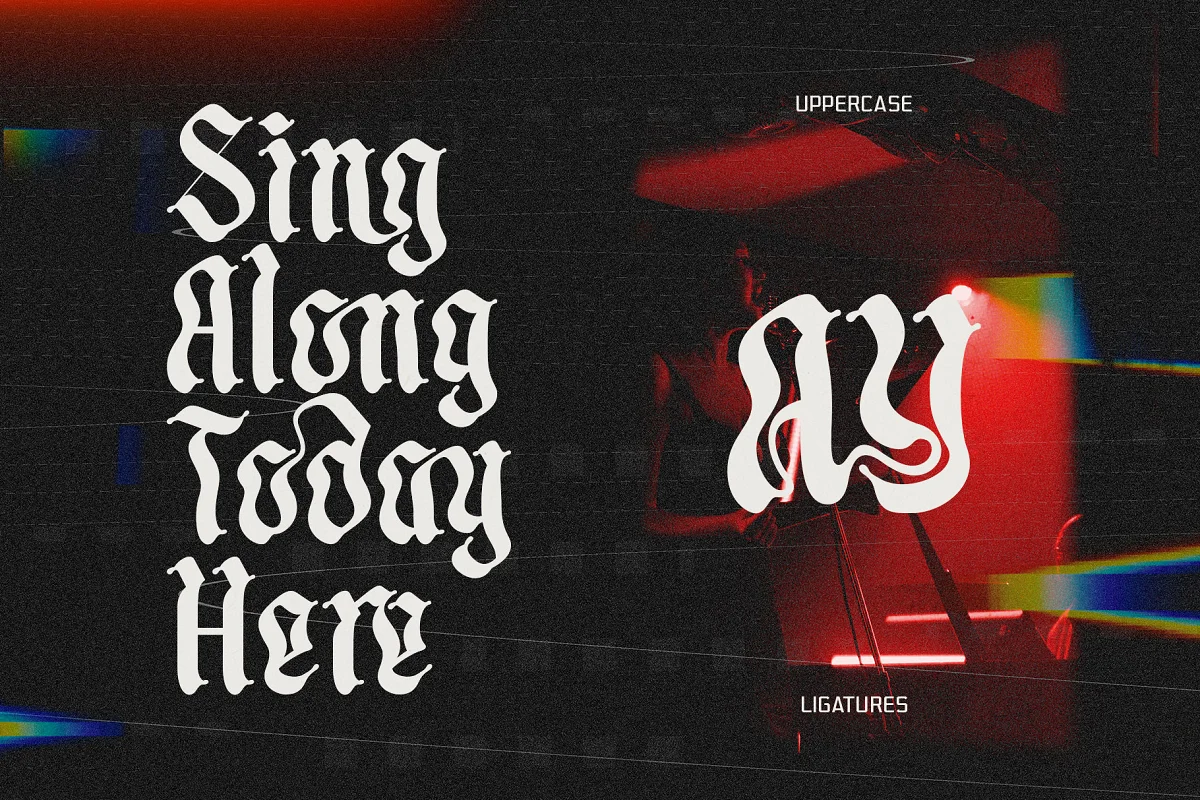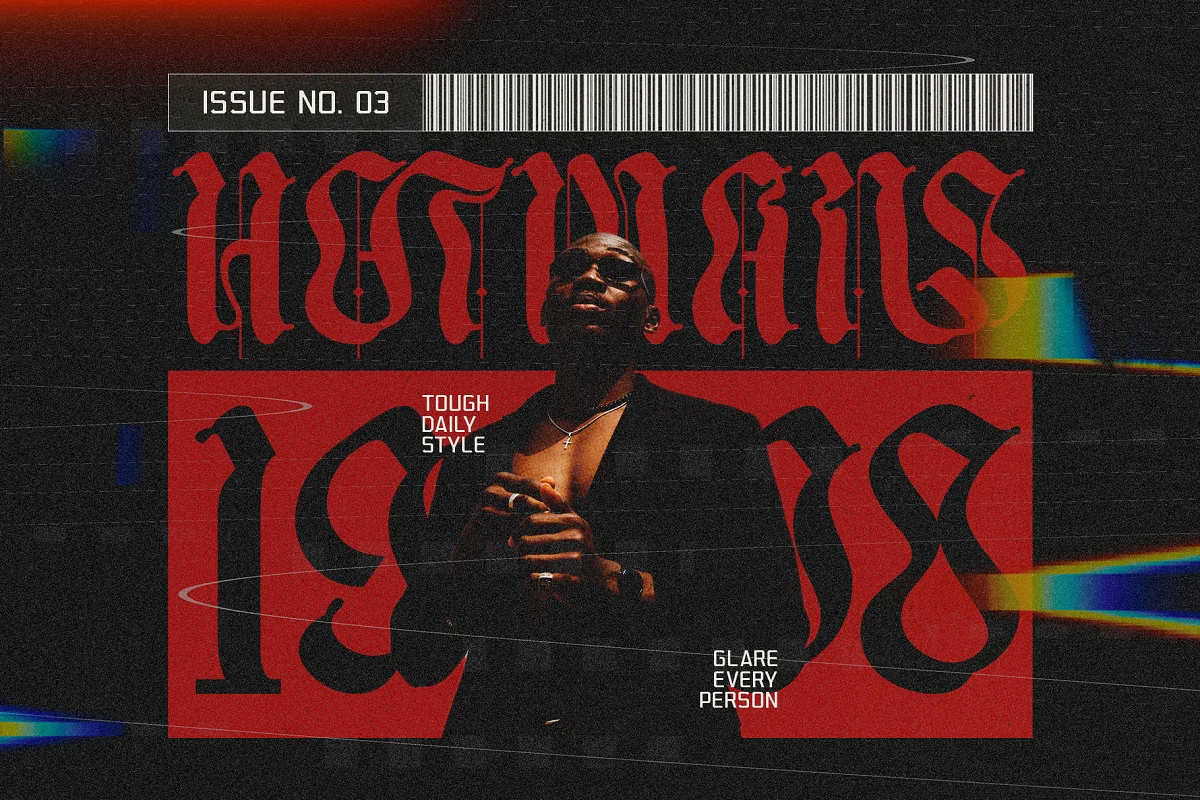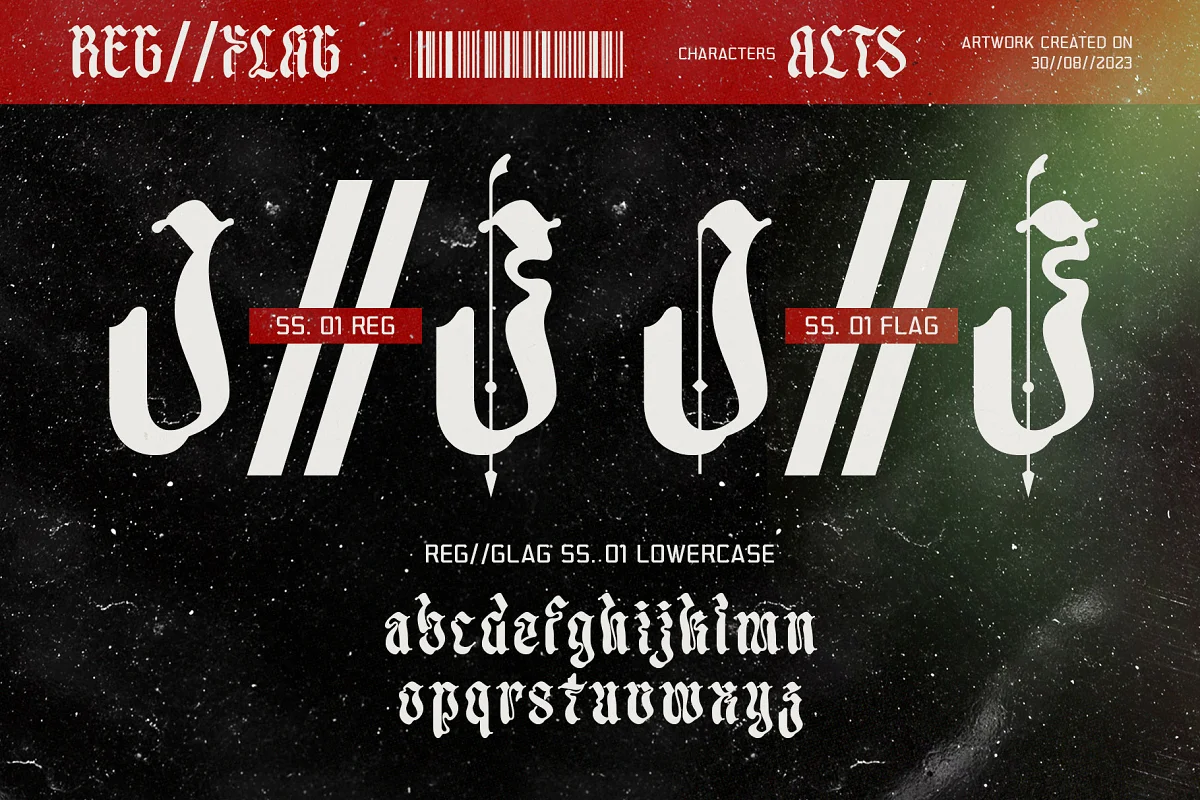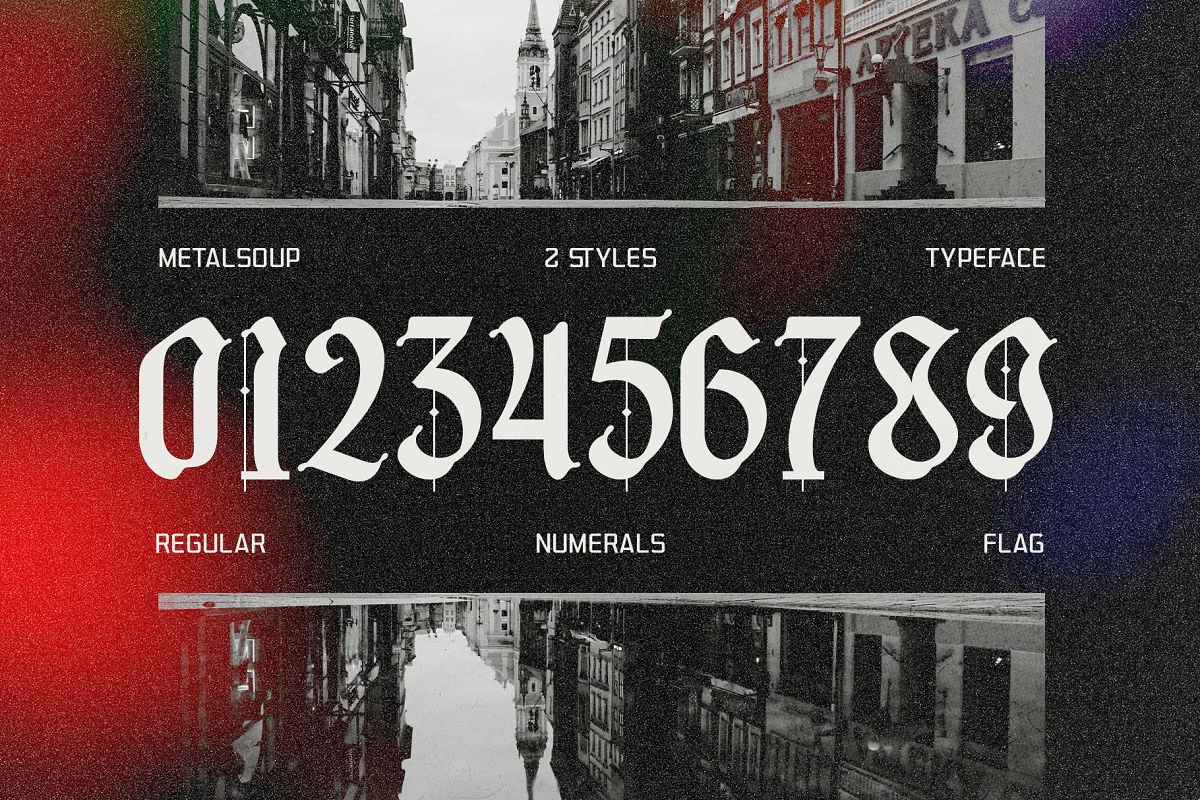
“Metal Soup” là một phông chữ blackletter quyến rũ, toát lên sự pha trộn độc đáo giữa sự táo bạo và nét thẩm mỹ năng động, tinh tế. Với thiết kế mạnh mẽ, phông chữ này hoàn hảo để tạo ấn tượng nổi bật trong các dự án thiết kế của bạn. “Metal Soup” tự hào có 720 ký tự và cung cấp hỗ trợ đa ngôn ngữ toàn diện, làm cho nó trở nên linh hoạt và có thể thích ứng với nhiều ứng dụng sáng tạo.
Các tính năng chính:
Kiểu chữ đen: “Metal Soup” có thiết kế chữ đen cổ điển, đặc trưng bởi những đường nét góc cạnh, sắc nét và các chi tiết trang trí công phu, mang lại cho văn bản của bạn cảm giác Gothic, thời trung cổ.
Phá hủy năng động: Phông chữ đã được chế tạo tỉ mỉ để kết hợp vẻ ngoài đau khổ, phong hóa. Mỗi chữ cái vẫn giữ được tính toàn vẹn trong khi vẫn có vẻ dũng cảm và hư hỏng, bổ sung thêm nét đặc trưng và cảm giác sóng độc đáo cho văn bản của bạn.
Bộ ký tự mở rộng: Với 720 ký tự, “Metal Soup” cung cấp hỗ trợ toàn diện cho nhiều ngôn ngữ và ký tự đặc biệt, đảm bảo văn bản của bạn trông tuyệt đẹp trong nhiều ngữ cảnh.
Ký tự thay thế: Phông chữ này bao gồm nhiều ký tự thay thế khác nhau, cho phép bạn thử nghiệm các dạng chữ khác nhau để đạt được tính thẩm mỹ mong muốn cho dự án của mình. Những lựa chọn thay thế này bổ sung thêm các tùy chọn linh hoạt và sáng tạo cho kiểu chữ của bạn.
Chữ ghép: “Metal Soup” có chữ ghép, là sự kết hợp được thiết kế đặc biệt của hai hoặc nhiều ký tự nhằm nâng cao sức hấp dẫn trực quan cho văn bản của bạn. Chữ ghép tạo ra một dòng chảy hài hòa và cải thiện khả năng đọc.
“Metal Soup” là một phông chữ linh hoạt và có hình ảnh quyến rũ, có thể nâng tầm các dự án thiết kế của bạn, cho dù bạn đang làm việc về xây dựng thương hiệu, bao bì, áp phích, thiệp mời hay bất kỳ nỗ lực sáng tạo nào khác. Phong cách chữ đen, tính năng phá hủy năng động, hỗ trợ đa ngôn ngữ, các ký tự thay thế và chữ ghép làm cho nó trở thành một bổ sung có giá trị cho thư viện phông chữ của bạn, cho phép bạn tạo ra các thiết kế độc đáo và bắt mắt, nổi bật giữa đám đông.
Hoàn hảo cho:
- Logo và Thương hiệu
- Tiêu đề biên tập
- Thiết kế poster
- Trang phục và hàng hóa
- Tiêu đề trang web
- Lời mời sự kiện
- và hơn thế nữa…